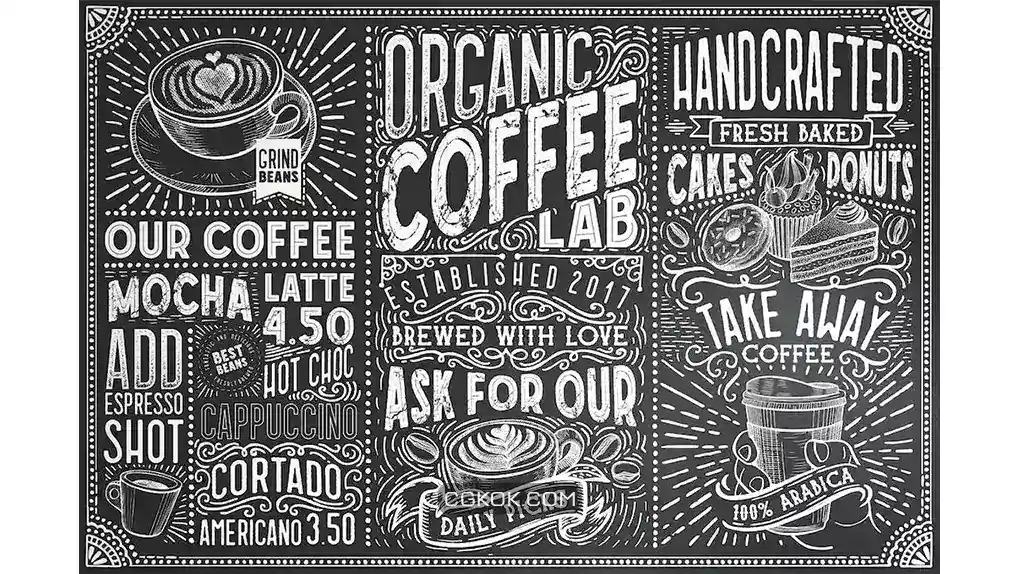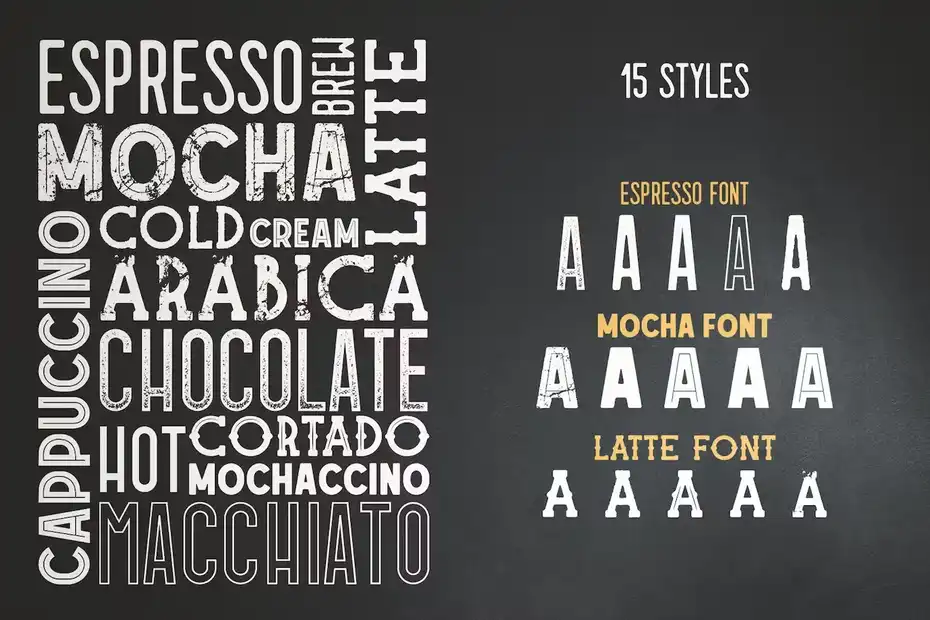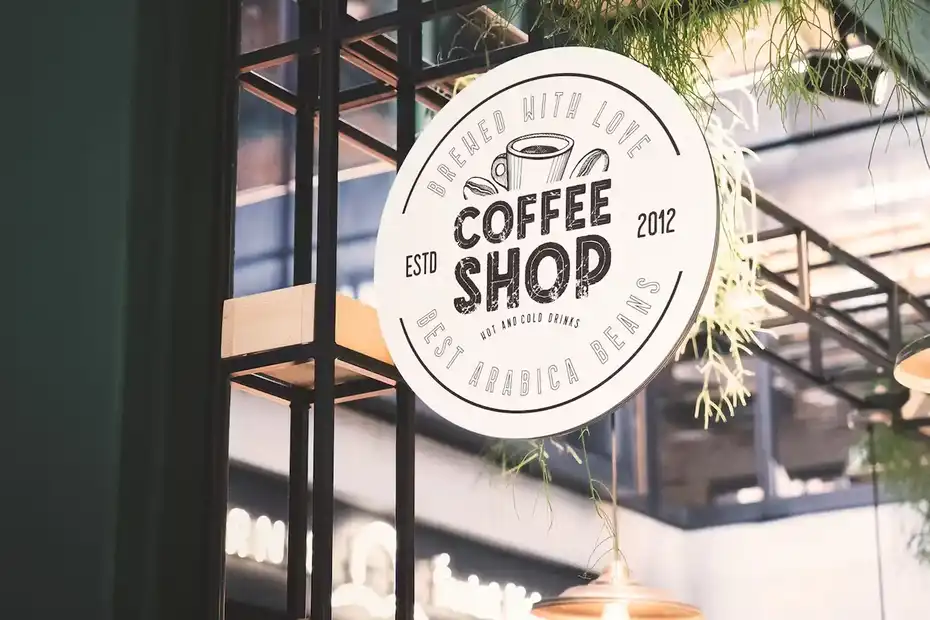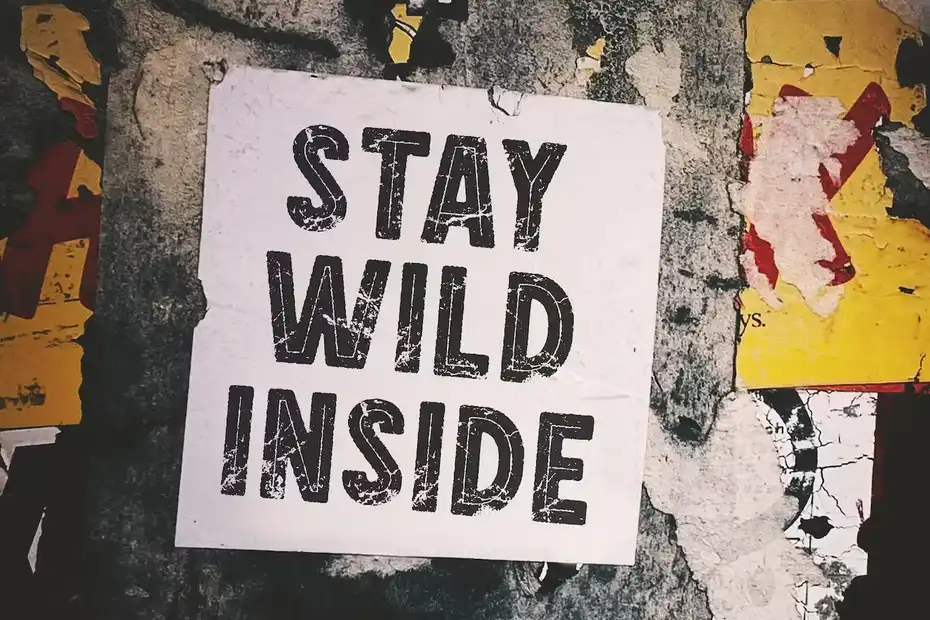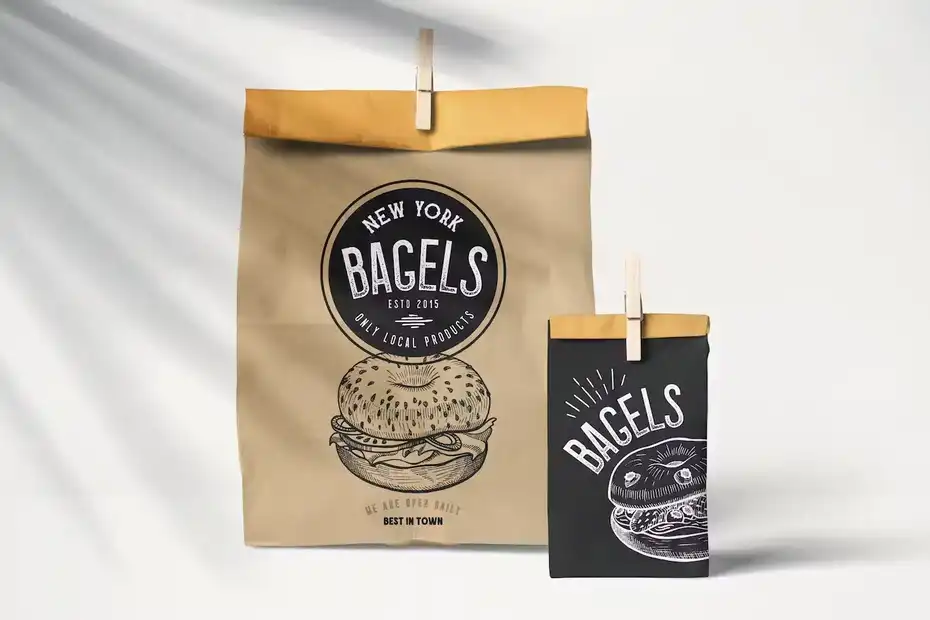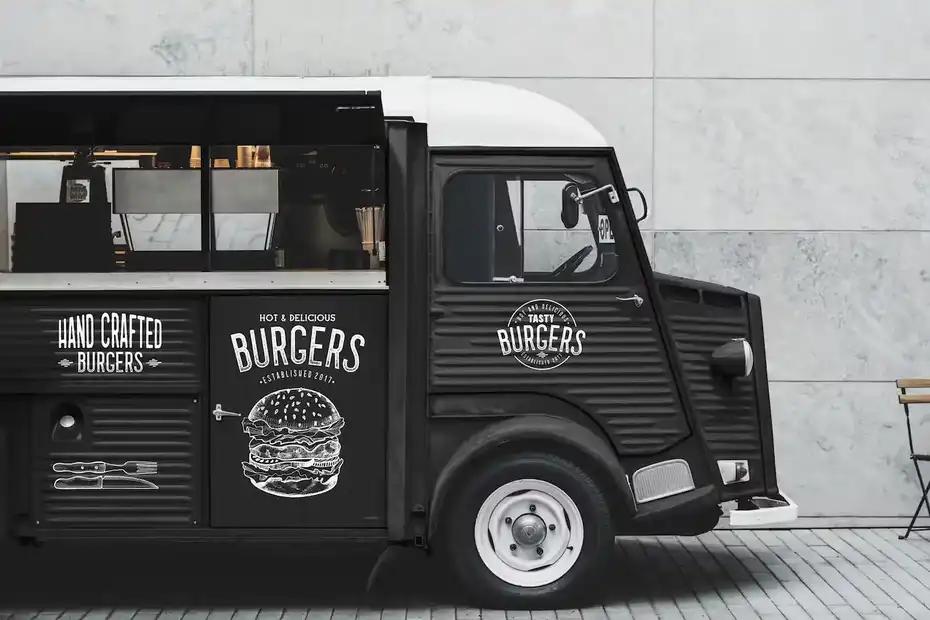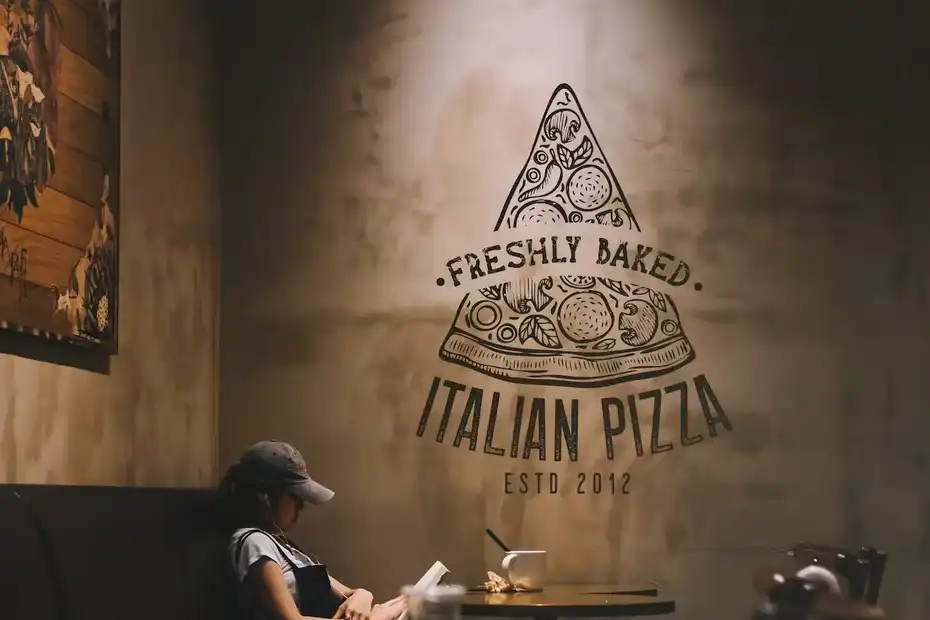
دانلود فونت کافی شاپ Fonts Coffee Lab Collection
دانلود فونت کافی شاپ Fonts Coffee Lab Collection : این مجموعه شامل 15 فونت انگلیسی کلاسیک کافه و فست فود است که میتوانید از آن در پروژه های خود استفاده نمایید.